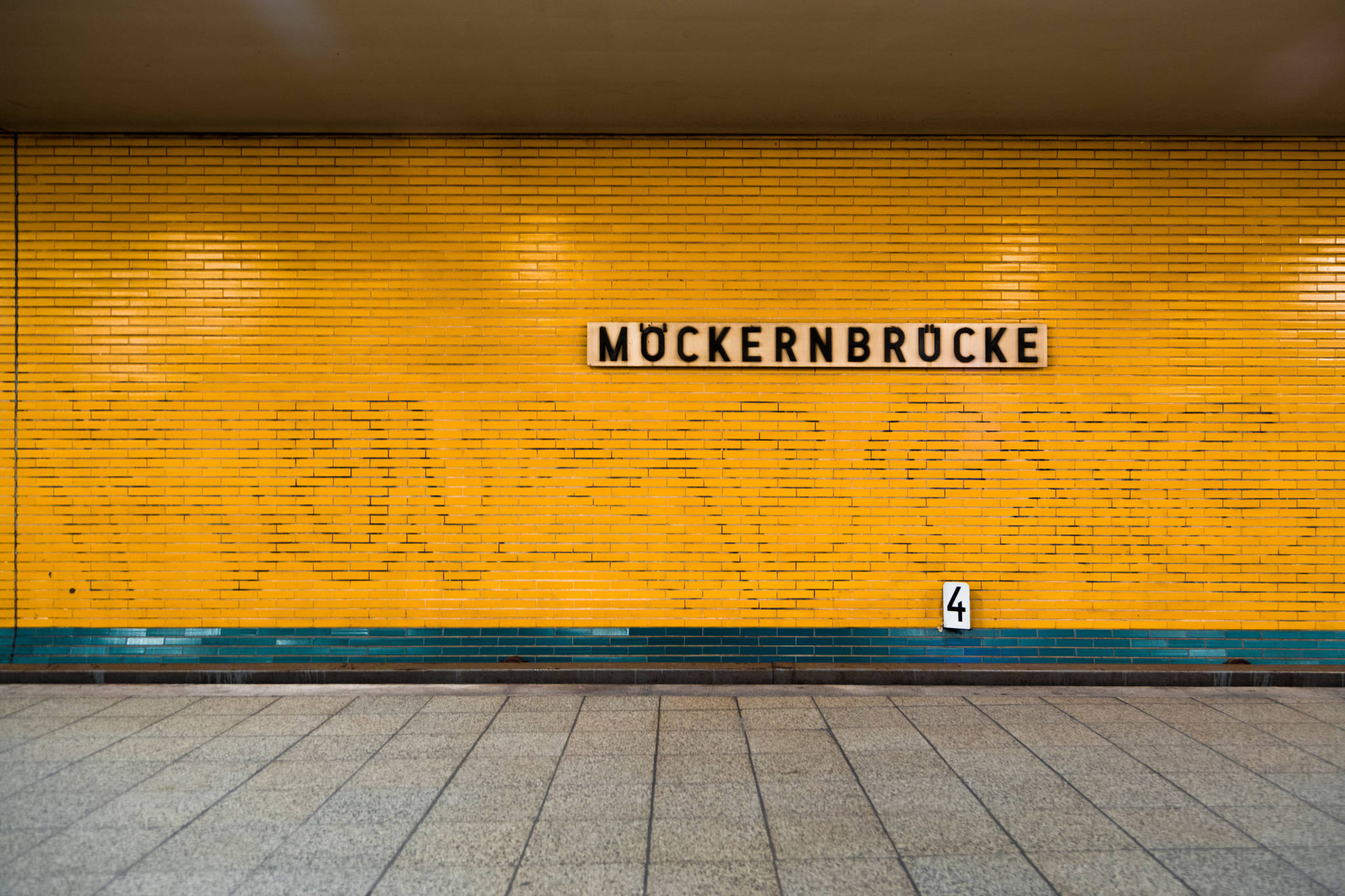
U-Bahn-Schriften (Berlin)
Wer weiß, vielleicht wird ja daraus eine ganze Buchreihe: "Subway Station Typography International"
… dann sollte ich mich mit meiner Bachelorarbeit wohl begannen bevor mir einer das Thema noch vorwegnimmt ;)
Lustig ist dass so ziemlich alle betroffenen "-strasse" Stationen von Rainer G. Rümmler entworfen und geplant wurden! Vielleicht mochte er das ß auch nicht so sehr ;)
Weißt Du, ob er als Architekt der Bahnhöfe Einfluss auf die Schreibweise der Namen an der Wand hatte?
Ich kann es nur vermuten, er war wie es heißt nicht nur für die Architektur sondern auch für die Gestaltung zuständig und bei ihm fällt es halt auf, dass (anders wie bei anderen Ubahnhof Gestaltern) oft viele verschiedene Schriften benutzt wurden die zum zu seiner Dekoration passten.
Während dies bei seinen ersten Entwürfen noch sehr dezent erfolgte, wie am Bayerischen Platz, wo er die Wände in Anlehnung an die bayerischen Landesfarben mit blauen und weißen Asbestzementplatten verkleiden ließ, wurde in den 1980er Jahren die Gestaltung immer pompöser. Viele Kritiker bemängelten, dass die eigentliche Funktion des U-Bahnhofes teilweise völlig in den Hintergrund trat und die Gestaltung mehr an Theaterkulissen denn an Verkehrsbauten erinnere.
Da sind nun zufällig die Stationen meines morgendlichen Arbeitswegs dabei, deshalb muß ich dazu noch einen Kommentar loswerden ;)
Über den Mehringdamm ärgere ich mich immer wieder. Nicht nur, daß ich die Schriftwahl für einen Faux Pas halte, der Bahnhofsname ist auch extrem schlecht zu erkennen, weil, wie man auf dem Foto schon sieht, immer nur ein paar Buchstaben hell erscheinen, und der Rest fast mit dem Hintergrund verschwimmt. Das ist aus jeder Perspektive so.
Daß die modernen Schilder leicht gebogen sind, hat ja meines Wissens genau den Grund, um Reflexionen möglichst auszuschalten, wie man beim Seestraßenschild sieht. Die Reflexion ist hier rechts nur noch als diffuser horizontaler Streifen bemerkbar.
Wenn ich dort morgens davor stehe, wundere ich mich allerdings immer, ob die Strichstärken der Buchstaben wirklich stimmen, das S und t sehen fetter aus als der Rest ;)
Daß es nicht die Frutiger ist, sieht man deutlich an den runden Punkten. Als die Schrift damals für die BVG benötigt wurde, gab es keine Frutiger Condensed, deshalb holte sich Meta Design von Adrian Frutiger das OK, eine schmalere Schrift basierend auf dem Design der Frutiger selbst zu entwerfen.
Also, die DEUTSCHE OPER sieht für mich aus mehreren Gründen wie ein gezeichneter Schriftzug und nicht wie eine Schriftvorlage aus: Das Stencil-D passt nicht in den Duktus des Restes. Das kantige U fällt gegenüber den runden Formen auch aus der Rolle. Ebenso das S mit Unterlänge.
Eine digitale Schrift, die Ähnlichkeiten mit den Formen des P und R (und nur mit jenen) aufweist, ist die Remah von Rosario Nocera (die muss man sich aber nicht merken …) sowie die ITC Stoclet.
Hallo Leute, ich melde mich mal wieder!
Entweder stehe ich total auf dem Schlauch oder ich bin zu Recht verwirrt (es ist das "a") …
Was ist das für ne Schrift?
Am 29. Januar 2016 um 14:45 schrieb RobertMichael:
.. davon ein fotoband mit schönen bildern und allen schriftennamen — ich würds kaufen.
Et Voilà:
Berlin unter Grund – Die Schriften der Berliner U-Bahn
„Berlin unter Grund“ nimmt den Leser mit auf eine Typotour durch das U-Bahn-Netz einer Millionenstadt. Die vielfältige Gestaltung der Stationen, die man so kaum in anderen Großstädten findet, zeigt wie sich ihr räumliches und typografisches Erscheinungsbild vom Deutschen Kaiserreich bis heute verändert hat. Anhand der Tafeln, die den Namen der verschiedenen U-Bahn-Stationen zeigen, erzählt das Buch ein Stück Typografie-Geschichte.
Weiß jemand, warum hier die Arnold Böcklin Schrift verwendet wurde. Böcklin und Wagner kannten sich, Böcklin mochte Wagner scheinbar aber nicht. Hat jemand hier noch irgendwelche Hintergrundinformationen?